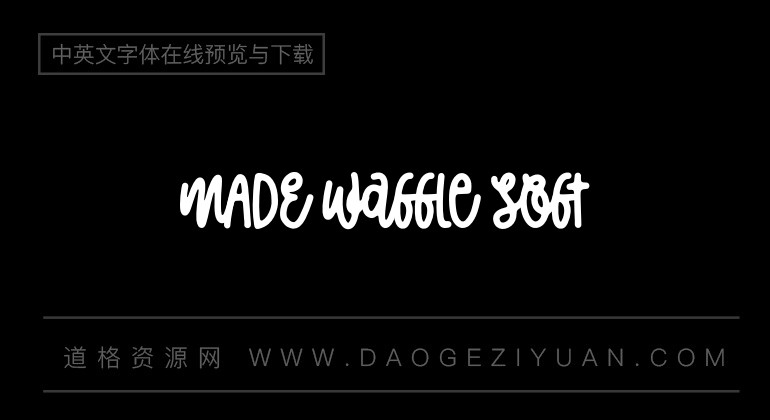
MADE Waffle Soft是由MADE Type设计师Eben Sorkin推出的一款柔软的字体,它是一款极具特色的,拥有温暖的视觉效果的字体。MADE Waffle Soft的字体特点是拥有温暖的视觉效果,拥有舒适的视觉感受,并且具有柔软的边缘,使用它可以营造出一种温暖、柔软的感觉。MADE Waffle Soft的字体也能够提供良好的可读性,并且具有清晰的字形,使得字体看起来更加清晰。MADE Waffle Soft也具有较高的可定制性,可以根据用户的需求进行定制,以满足用户的不同需求。内容介绍
MADE Waffle Soft是一款非常不错的手写艺术字体,具有很好的视觉感,适合于文化类的宣传设计、商业类品牌的广告和产品包装设计以及个性化文字排版等较多场景。